日本首席体力活儿设计师——新村则人
新村则人先生出生于一个小渔村,继承了渔民身上特有的敦厚,这一点从他的面相上就看得出来。但你不知道的是,在这张朴实的面孔下隐藏着一个拥有巨大创造力的手工狂魔。
“真实感”是新村则人在设计中永恒不变的追求,为了在设计中表现出真实的质感,他会做出许多你无法想象的惊世之举。下面是他为日本杂志《野性时代》设计的一组海报,我们来感受一下这种疯狂。
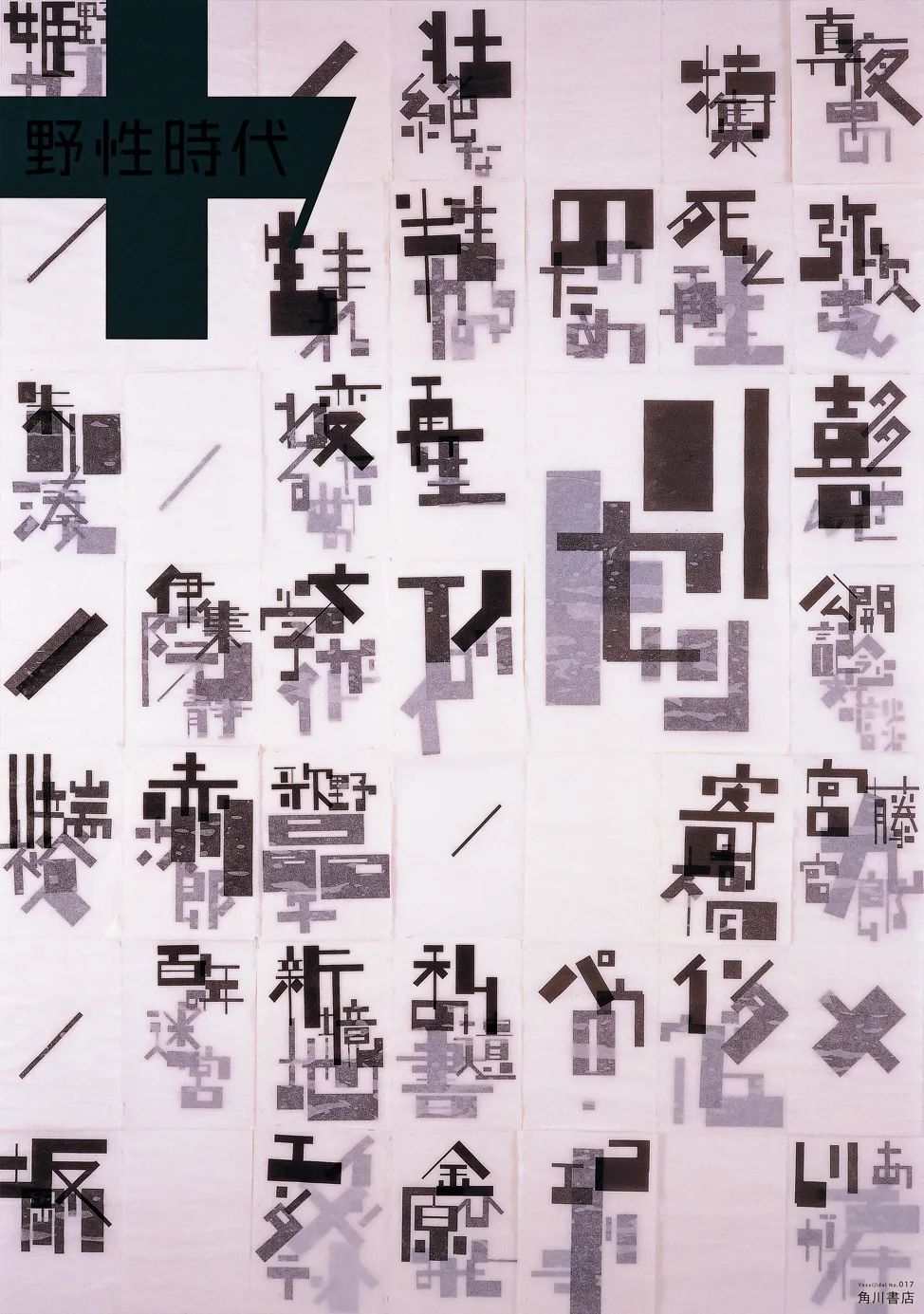
在这张海报中,新村则人将几张印有文字的宣纸重叠在一起,再刷上一层水,使宣纸变得透明,下面的文字就会从不同层数的宣纸后面透出来,呈现出深浅不一的视觉观感。虽然这种层次感用软件可以轻易实现,但在细节与质感上与手工制作有着云泥之别。
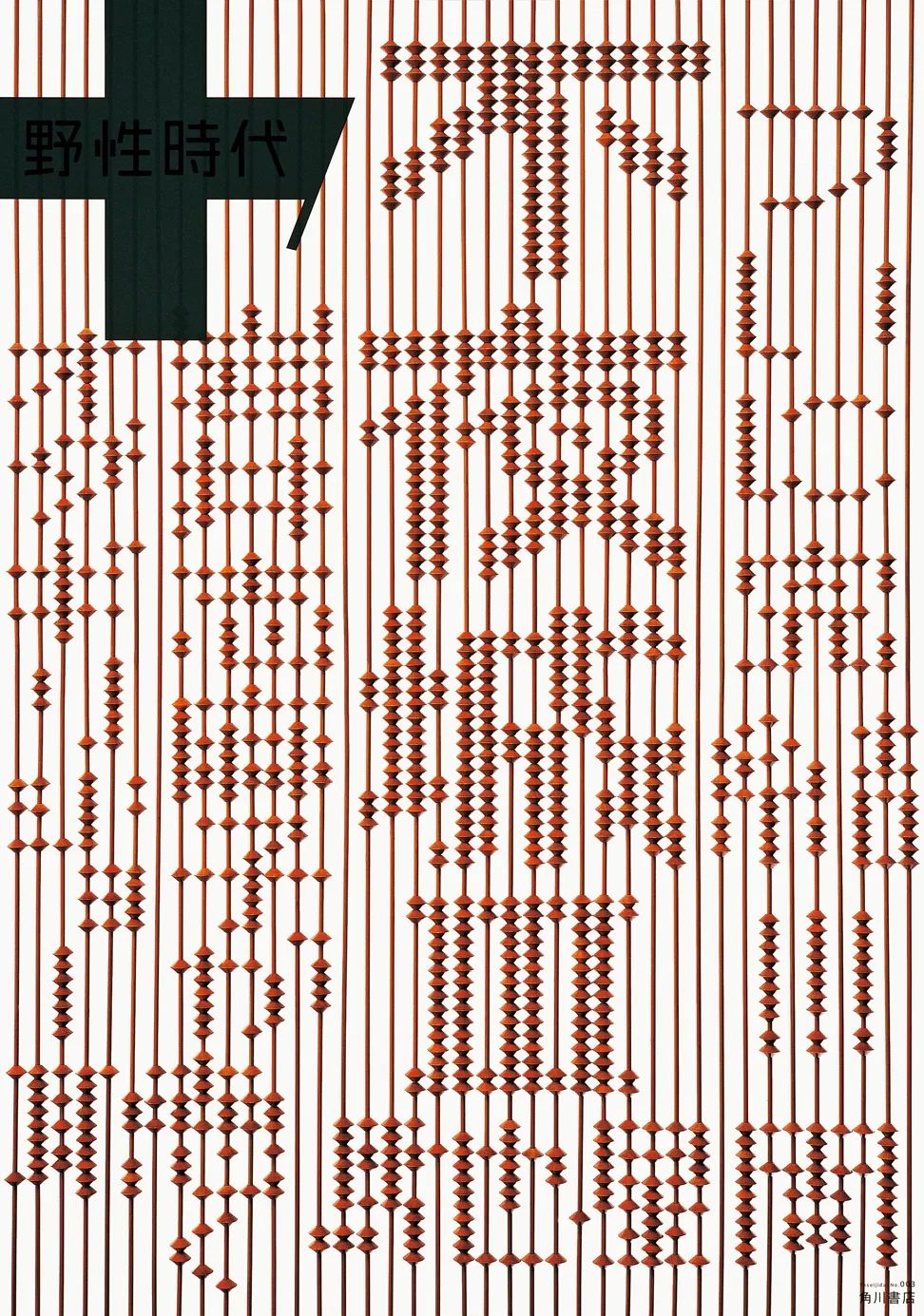
这幅海报是他花了十个小时,用真实的算盘珠拼成的,个别珠子上微妙的小偏差可以透露出这不是一张电脑制作的图片。
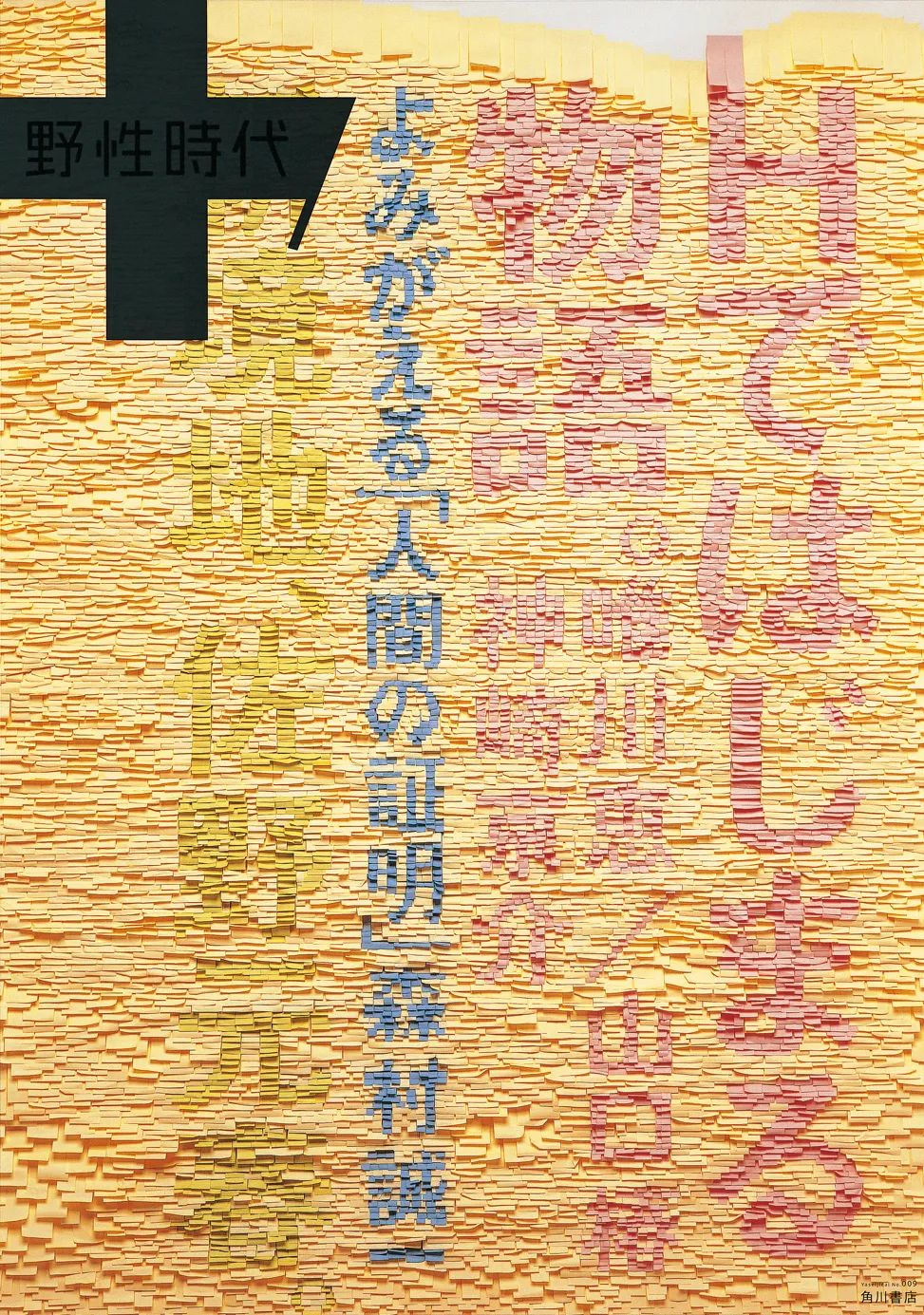
你猜往墙上贴一万张便签纸需要多久?答案是15个小时。我在想如果是我贴完了这张海报,后退三步观察一下,发现配色不太理想,我应该会真实的死亡。除此之外,他还用了拧气球和刺绣等方法制作了一系列的海报,着实是一个多才多艺的手工小能手。
为了追求真实的效果,诸如此类的爆炸行径后面还有很多,而且会愈演愈烈,甚至达到了“以真乱假”的地步。比如下面这张。
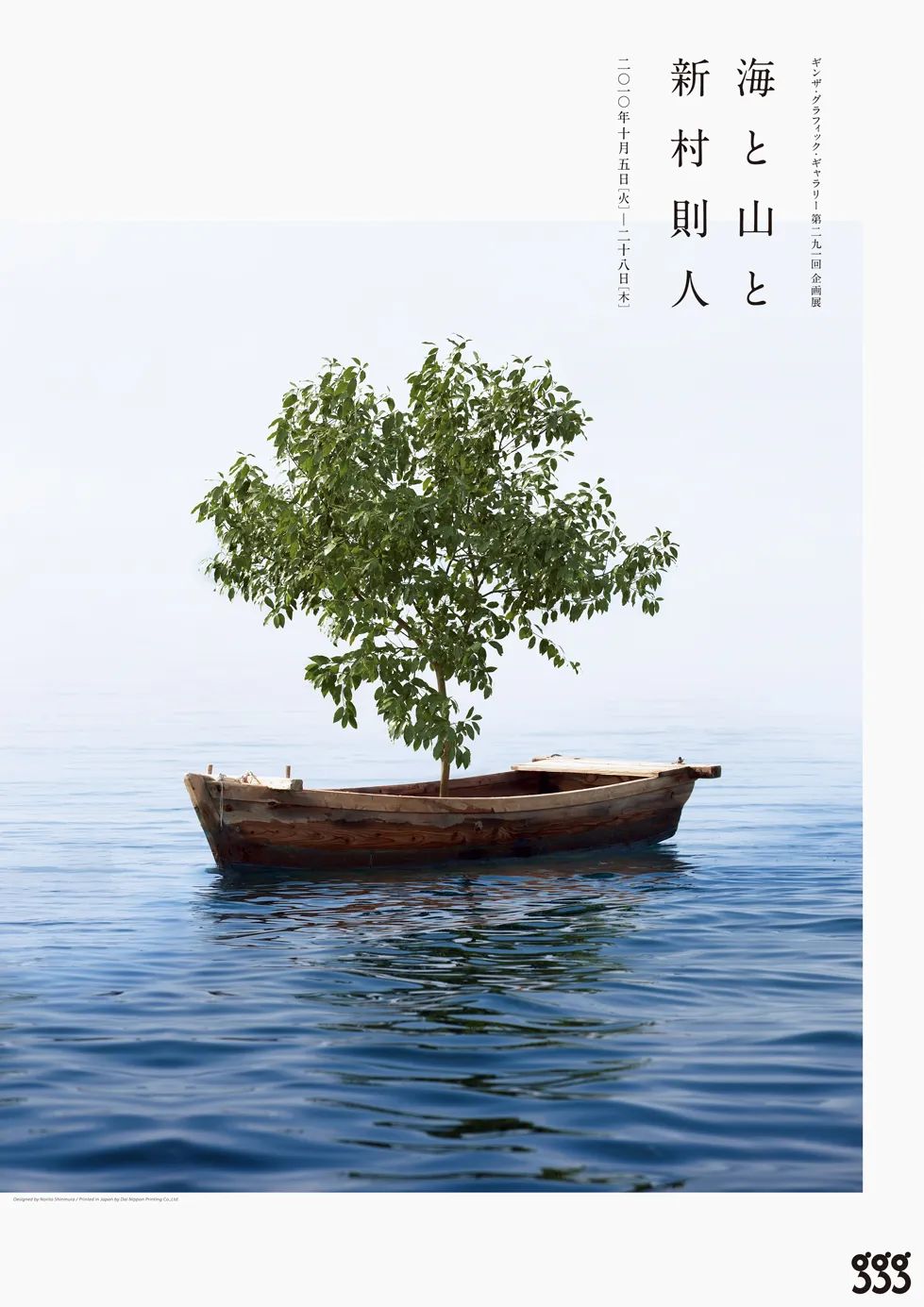
银座ggg展海报(2010)
当我看到船上有一棵树的时候,我的第一反应是照片合成,但这一棵是新村则人放上去的。若要颁发一个全日本“最实在设计师奖”,我推新村则人,你也很难找到第二个能与他抗衡的入围者。
新村则人认为,有些年轻的设计师会苦于没有灵感,其实只要平时注意从身边找到自己喜欢的东西就行了,只要你对其产生热爱,在设计中就会很容易找到契合点,并设计出只属于自己的东西。属于自己的好的创意,往往能填补技法水平不高的劣势。
我觉得他的意思是,设计讲究的更多是想法而不是技法。再通俗点就是,你也不会用PS么?那我们一起来做手工吧!
新村则人还说过,“我20岁那年还不知道设计是什么,做出来的东西很差劲。当然,我现在做出来的东西依然很差劲。”
这句话就很幽默了,他做很差劲那我们做的是什么垃圾,嗯?
获得奖项
其他各类奖项还有很多,这里不一一列举,同时新村则人也是东京TDC,纽约ADC,JAGDA等机构的会员,以及2000年富士ADC、2001年纽约ADC、2002年JAGDA等设计大赛评委。
设计师简介
新村则人,1960年5月5日出生在日本山口县大岛郡浮岛的一个渔民家庭,家中有兄弟姐妹共八个人,新村则人是最小的。作为家中的小儿子,同时又生活在海边,可想而知他的童年生活浪得有多开心。
日本的“县”大致相当于中国的“省”,山口县位于日本本州最西端,三面环海形如半岛。
新村则人的老家大岛郡位于山口县的最东边,是一个小岛,浮岛是上面更小的一块小岛,而他就是这座岛上的岛民。
为什么这么仔细介绍地理知识呢,因为新村则人出生的小渔村只有2000人,那里有最淳朴的民风,同时优越的地理位置造就了丰富的物产和优美的自然环境。新村则人常说他的灵感都是来源于生活,这跟家乡带给他的滋养密不可分。人与自然的关系是他设计中永恒不变的主题,这一点在他的许多作品中都有体现。
爱上设计与一位美术老师的启发有关,小学4年级时,新村则人受到伊藤哲老师的影响,迷上了海报艺术,並立志成为一名设计师。
他从自己的成长的环境中逐渐发现了如何寻找创意,如何让自己的创意简洁再简洁,直到小学生也看得懂。
下面是新村则人为自己家的新村水产拍摄制作的一系列海报。你能从中感受到这种简单直接的设计力量。
这一组海报是为新村水产的海鲜都打上了高级产品才会有的品牌标签,让它们看起来也像是高级螃蟹和高级鱼,以表达海鲜品质上乘的概念。
这一组的主题“网”,是新村则人在看到自己的父亲修补渔网时有感而发,生出的创作灵感。这里强调一下,本篇文章出现的所有疑似电脑合成的设计作品,都是实拍完成的。不过下面这一组海报的制作方式确实遭受过质疑。
“水滴”,新村则人曾公开解释过这组海报的制作过程,将水产上方叠放三层玻璃,每一层都用水滴滴出“新村水产”的字样,然后在拍摄时将焦面对在第二层玻璃上,就能拍摄出这样的效果。建议放大观看。所以收起你们的高斯模糊,不要对手工狂魔的实力存有质疑。
这鱼飞得这么飘逸也是实拍么?这一组的主题是“岛上的渔夫”,这些渔夫都是新村则人的亲戚。一开始我还以为他们是把鱼扬到天上,后来一想那画面太美,确实是不敢看。其实这些鱼是在游,镜头是透过一个清澈的鱼缸在拍摄,仔细看后面海面的畸变,就能发现其中的端倪。为了呈现最新鲜健康的鱼,他们带着鱼缸跟随渔船出海打鱼,在船上完成了实景拍摄。构图的话,应该是由鱼们自己把握的。
“大渔舞”,画面中心的环形水流是请了14艘渔船在海面上开出来的,放大后能看到渔船,实拍。
新村则人一直保持着一个习惯,就是将设计完成的作品第一时间拿给自己的父母过目,因为他们是纯粹的渔民,对设计一窍不通,“若他们都能理解我作品的含义,那么我相信不分职业,不同种族的人都可以理解。” 这也造就了新村则人的作品风格:简洁明了,贴近生活。
1980年,新村则人毕业于大阪设计师学院,毕业后一直在大阪工作,直至1984年加入了梦寐以求的东京松永真设计事务所。此后又先后就职于Taki公司和I&S/BBDO公司。
1995年,新村则人创立了自己的设计工作室Shinmura设计公司。主要为SHISEIDO(资生堂)旗下两个品牌ELIXIR和INOUI ID从事设计,也为ZEN香水品牌担当广告设计,同时作为艺术总监担任Muji Campsite(无印良品露营地)的广告及其他工作。
作品解析
百年后海考〈1997〉
这是新村则人为山口县渔连设计的一组海报,目的在于提醒人们保护森林、保护鱼类。
上面的海报是这一系列中最知名的一张。有一次新村则人从电视节目中了解到,森林采伐是海鱼减少的一个重要原因,于是他专门收集了一些树叶,把叶子放在一个空旷的背景上,末端伸出一个鱼的尾巴,乍看去两者便形成了一尾鱼的形状,形象地表现出森林与鱼类唇亡齿寒的关系。
“这是我至今为止最满意的作品,从这张作品开始,我认识到要利用身边的东西作出设计,因为熟悉,所以人们更加容易理解你要表达的理念,这样才能达到宣传的效果。”
上面是这系列中的其余几张,其实单看画面就不难理解他想表达的意思。如果还是不确定的话,再教你一招。以第一张为例,一根鱼线上面挂着几十个鱼钩,我把下面文字中仅认识的几个汉字提取出来是,“鱼的子孙”,“获”。翻译过来就是,按照这个钓法,鱼都让你们钓得断子绝孙了。是不是很好理解?后面几张你可以自己试试。
全球气温上升〈2005〉
这张海报中的文字还是用上面的方法阅读,只挑你认识看就行,大概意思就是说全球气温上升的危害,它将导致海平面上升,多少陆地会消失,多少人们会流离失所。这段危害的文字还没来得及看完,就被不断上涨的水面吞没了。
这幅作品除了顶级的创意之外,也几乎是新村则人手作海报的巅峰。不用不相信自己的眼睛,这张海报是手工制作的。新村则人在工作室里特制了一个玻璃水缸,然后将文字部分一个一个剪下来放入水中等待其沉没,并伺机拍摄,就是这么硬核。
山口县幼儿园〈2005〉
山口县幼儿园是建筑师窪田勝文的作品,在标志设计方面他找到了新村则人。
是不是觉得设计大师的钱好赚?但我觉得这个设计非常好,既像一个蛋,又有襁褓和保护的意思,给人一种天然的安全感,同时也符合新村则人一贯的设计风格,简单直接,返璞归真。
即便我强行解释,还是觉得画个椭圆就收钱有点坑?那你仔细观察一下,能看出它跟一般椭圆的区别么?
我在标志上面叠了一张品红色的椭圆,你会发现把圆压扁并不能与它完全重合,这个标志的曲率有经过特别的调整。
简单来说,椭圆更“尖”而它更“顿”。我觉得这会使它看起来更柔软,却又更坚固。窪田勝文在委托新村的时候还提出了另一个要求,希望孩子不要撞到门上的玻璃。于是,新村将标志延展成了一个防撞的设计。
两扇玻璃移门分开的时候是标志,重叠的时候就变成了小动物的脸。可爱么?
2016奥运会“候选人档案”〈2008〉
当时国际奥委会确定的2016奥运会最终候选人有:里约热内卢,芝加哥,马德里和东京。日本的候选人档案由新村则人负责设计。
设计中采用了满满的日本特色,用绸缎将画册像礼物一样仔细包起来,更值得一提的是它使用了日本德岛的“阿波和纸”以及日本传统的装订方式。
这种装订方式最大特点我想你应该能猜到。
于是日本动员了全国的装订工人来陪他做手工。新村在为这个项目做提案的时候还紧张够呛。最终结果我们都知道了,巴西当选,日本重在参与,只能心疼两秒。
森の薪能〈2008〉
在日本有一种传统的歌舞剧叫“能剧”,演员会带着面具拿着扇子,在舞台上发出一些神奇的声音,真的是非常高能。有机会你可以现场体验一下,因为我也是瞎说的,我没看过。
这一场能剧的主题是“森”,于是新村将叶子拼贴在能剧常用的道具扇子上,将森与能的概念合二为一。
花束餐巾〈2009〉
一个有趣的小设计,不需要解释,看图就能秒懂。